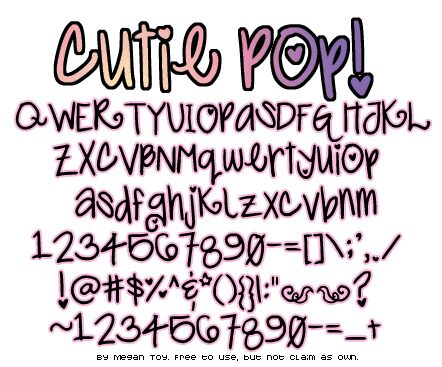
Cutie Pop von Megan Toy ist eine kostenlose, handschriftliche Display-Schrift mit hohen, locker gezeichneten Buchstaben und einem beschwingten, markerartigen Strich. Ihre unregelmäßigen Kurven verleihen dem Schriftbild eine wahrhaft persönliche Note.
Designer, die an Projekten für Kinder oder im Bastelbereich arbeiten, können sie für Party-Einladungen, Scrapbook-Seiten und verspielte Verpackungen einsetzen. Die abgerundeten Formen und die lebendige Grundlinie passen zu fröhlichen Themen, besonders wenn die Beschriftung wie eine schnelle, handgezeichnete Notiz wirken soll. Am überzeugendsten wirkt sie auf Einladungen, wo ihr zwangloser Schwung Teil der Feier selbst werden kann.